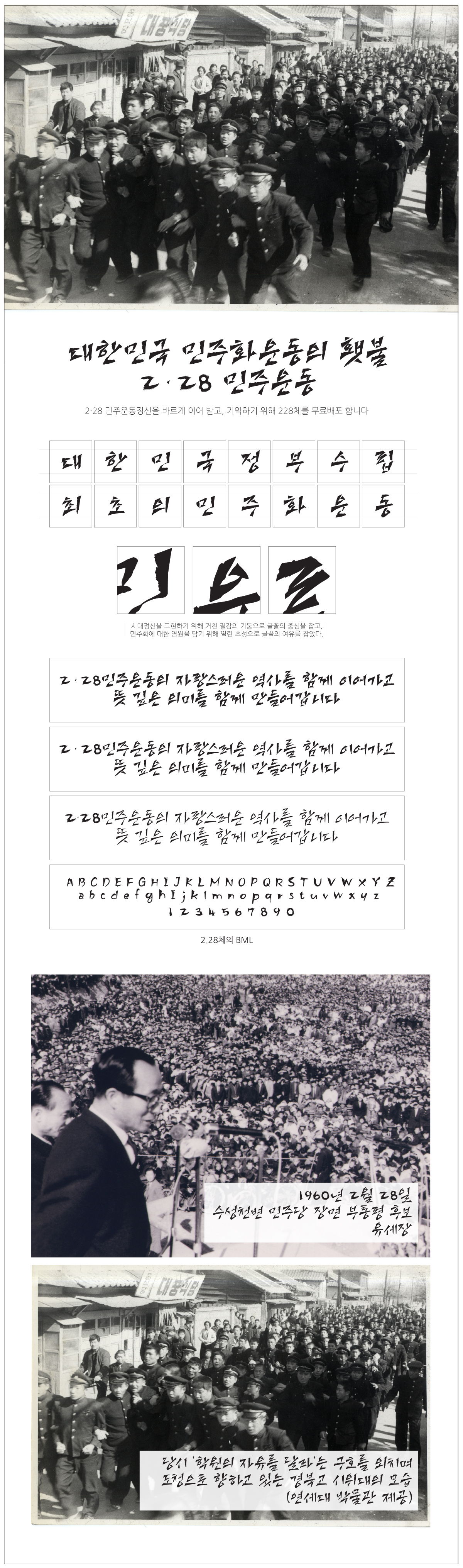
다온폰트 '228'는 B, M, L 3가지 버전으로 출시 되었습니다.
폰트의 구성은 한글 2,350자의 한글과
영문, 숫자, 특수문자 일부로 구성된 폰트입니다.
이번 업데이트 된 다온폰트 '228'체는 2.28 민주운동정신을
바르게 이어 받고
기억하기 위해 무료로 배포합니다.